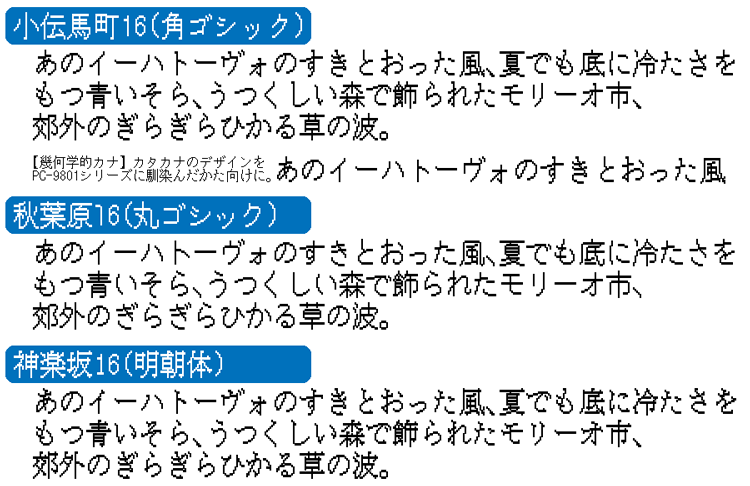
KHドットフォントシリーズは、昔懐かしいドットで構成されたビットマップフォントです。15種類の書体がセットになっています。1991年から1996年にかけてデザインされた、高品質なフォントです。12ピクセル、16ピクセル、24ピクセル、36ピクセル四方で構成された、個性的な15の書体です。
小伝馬町12 / 幾何学的カナ / 小かな (角ゴシック)、神楽坂12 (明朝体)、道玄坂12 (太明朝体)
小伝馬町16 / 幾何学的カナ (角ゴシック)、秋葉原16 (丸ゴシック)、神楽坂16 (明朝体)、道玄坂16 (太明朝体)、人形町16 (教科書体)、八丁堀16 (隷書体)、兜町16 (ファンテール)
日比谷24 (明朝体)
日比谷32 (明朝体)